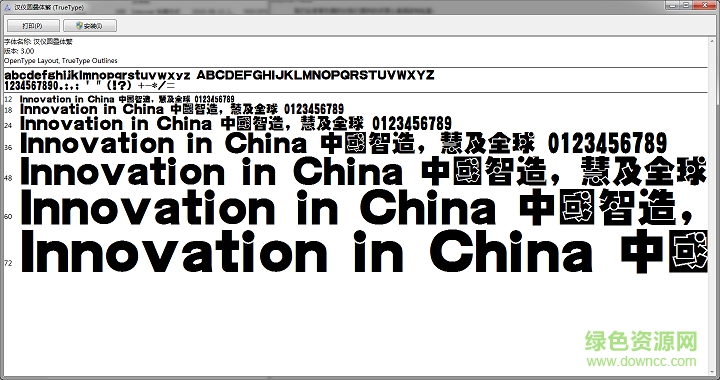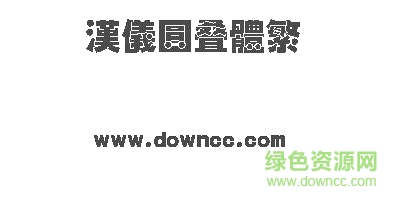
hyb8gf是什么字體?hyb8gf是漢儀圓疊體繁體字體,布白均勻,飽滿晶瑩,閱讀效果好,欣賞價值與實用性兼?zhèn)?,有需要者快來資源網(wǎng)下載各類個性字體吧!
該字體線條非常的粗壯,字形端正大方得體,可以廣泛應用于廣告設計、宣傳海報、ppt、影視制作以及任何使用文字的領域!
它運用夸張、明暗、增減筆劃形象、裝飾等手法,以豐富的想象力,重新構成字形,既加強文字的特征,又豐富了標準字體的內(nèi)涵。同時,在設計過程中,不僅要求單個字形美觀,還要使整體風格和諧統(tǒng)一,理念內(nèi)涵和易讀性,以便于信息傳播。